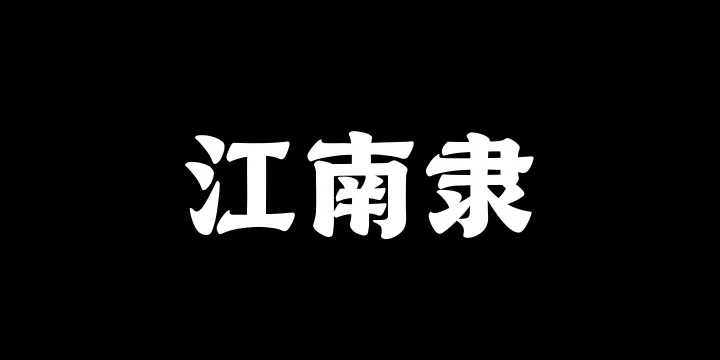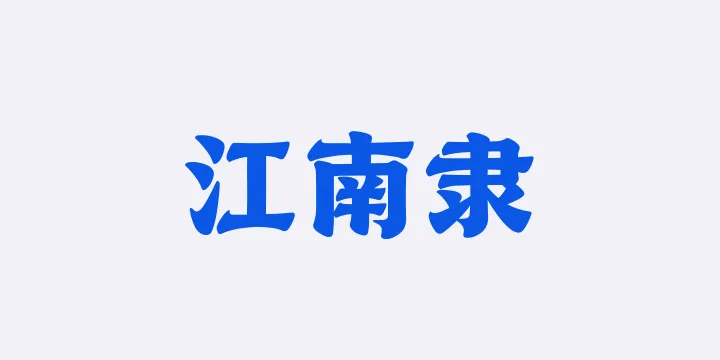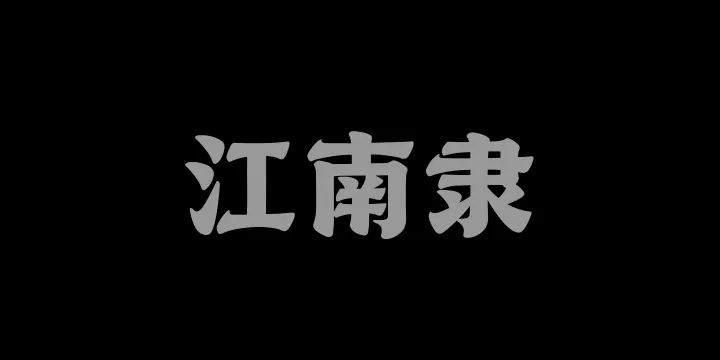
字体全名: 山海江南隶95W
字体简介: 山海江南隶95W,是一款全新的楷体字体,是山海江南隶字体家族系列中的特粗款,编号95W,包含汉字9169个,符号200+个。该字体字形优美文雅,诗意内敛,整体以隶书为骨,字形扁方,取正势,重心平稳,结体紧实,横平竖直,隶书的运笔走势蕴含其中,流畅自然,蕴含东方审美韵味,尽显优雅从容,秀雅清新。